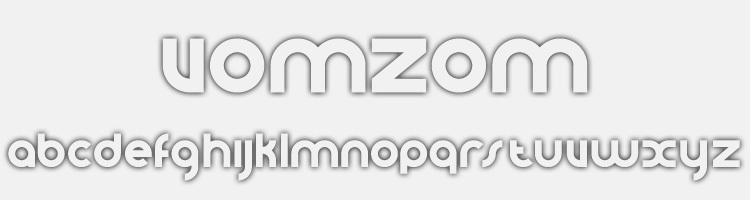
خط VomZom من Defaulterror هو خط عرض هندسي عصري ومجاني، يتميز ببناء ناعم ومستدير وهدوء مستقبلي طفيف. تم اختزال الحروف في منحنيات جريئة ووصلات بسيطة، وتضفي الأشكال الدائرية والأقواس المنخفضة والسلسة طابعاً ودوداً واصطناعياً حتى على الأشكال الأكثر حدة.
يتناسب هذا الخط بشكل طبيعي مع الأعمال الفنية الموسيقية، والعلامات التجارية لألعاب الأندي، وعناوين الملصقات، وشاشات بدء التطبيقات، والأسماء القصيرة على العبوات، حيث يمكن لخط مجاني يتمتع بهذا القدر من التشكيل أن يحدد الحالة المزاجية بالكامل. استخدمه عندما تريد أن تعطي بضع كلمات طابعاً مرحاً ولكن مضبوطاً، خاصةً في أغلفة العناوين وبطاقات العناوين، حيث تعمل منحنياته العريضة وإيقاعه المدمج بفاعلية بسرعة.
Vomit Zombie هي علامة تجارية للملابس أعمل عليها حالياً مع Ekon. نشأ خط VomZom أثناء محاولتي ابتكار شعار لهذه العلامة.